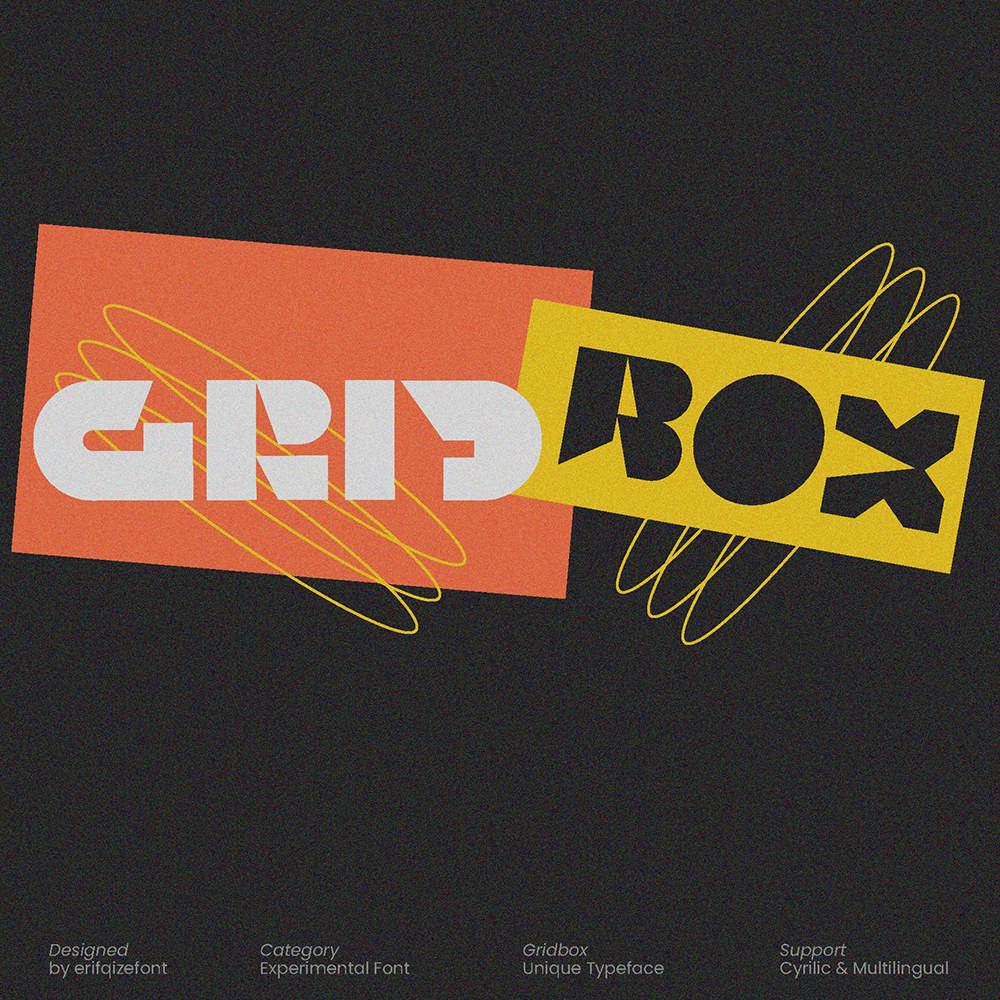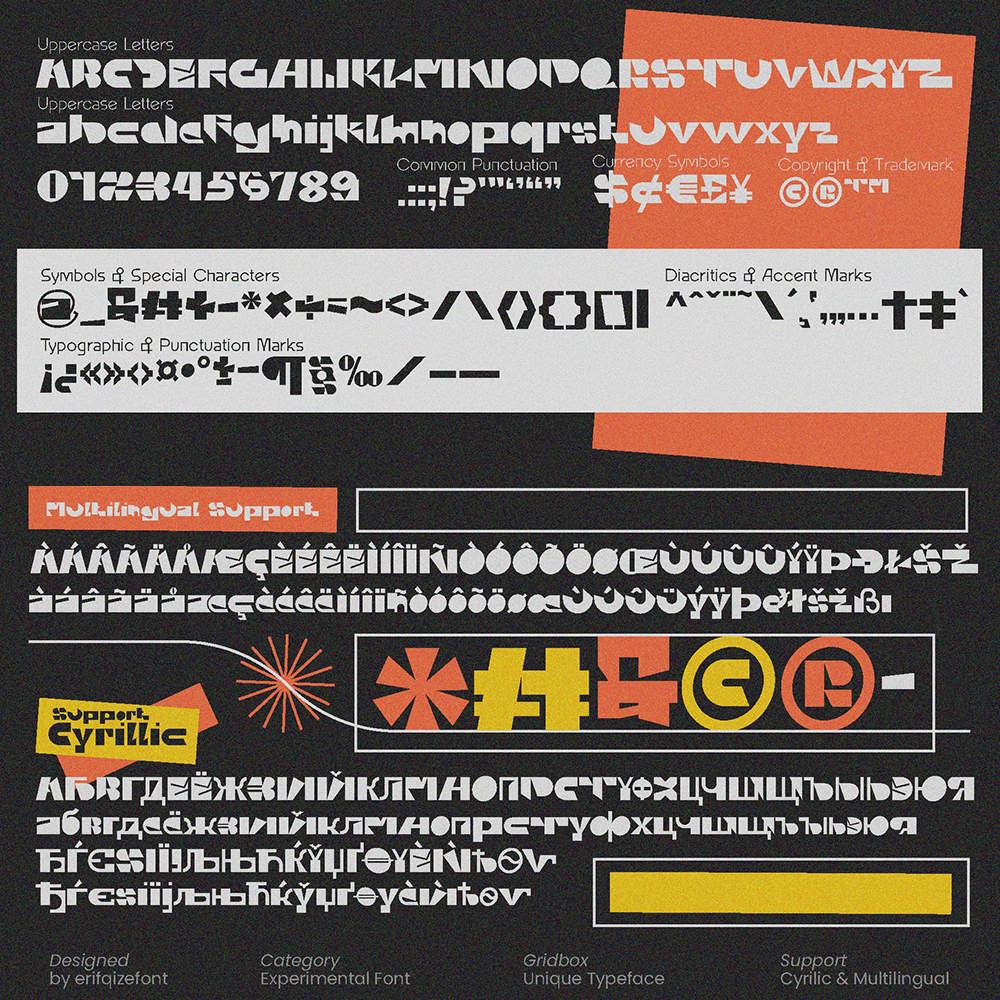
فونت پرمیوم و انگلیسی Gridbox Font یک فونت جسورانه و تجربی است که برای جابهجایی مرزها طراحی شده است. هندسه تیز و اشکال نامتعارف آن به هر کاراکتر، شخصیتی قوی و سرکش میدهد و ایدهآل برای پروژههایی که توجه را میطلبند میباشد. چه در حال ساخت یک برند آیندهنگر باشید، چه در حال خلق جلد آلبوم یا طراحی طرحبندیهای سرمقاله، گریدباکس اصالت چشمگیری را به تایپوگرافی شما میآورد.
- ۲ سبک معمولی و ایتالیک با گلیف های استاندارد